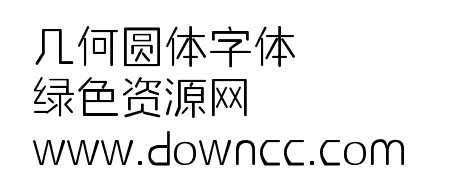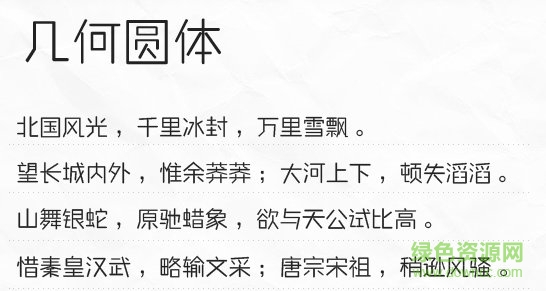
幾何圓體是一款字跡端正、造型精簡(jiǎn)大氣的幾何字體系列,有著書(shū)寫(xiě)筆直、字跡穩(wěn)健的視覺(jué)體驗(yàn),讓文字設(shè)計(jì)更加端方嚴(yán)謹(jǐn),綠色資源網(wǎng)誠(chéng)意推薦!
幾何體讓漢字內(nèi)部更加有規(guī)律,也能簡(jiǎn)化出一部分空間出來(lái),讓人看上去也比較干凈清爽有利于閱讀,當(dāng)然也有利于教學(xué),從思維深層次考慮讓人思維清晰也更有原則。